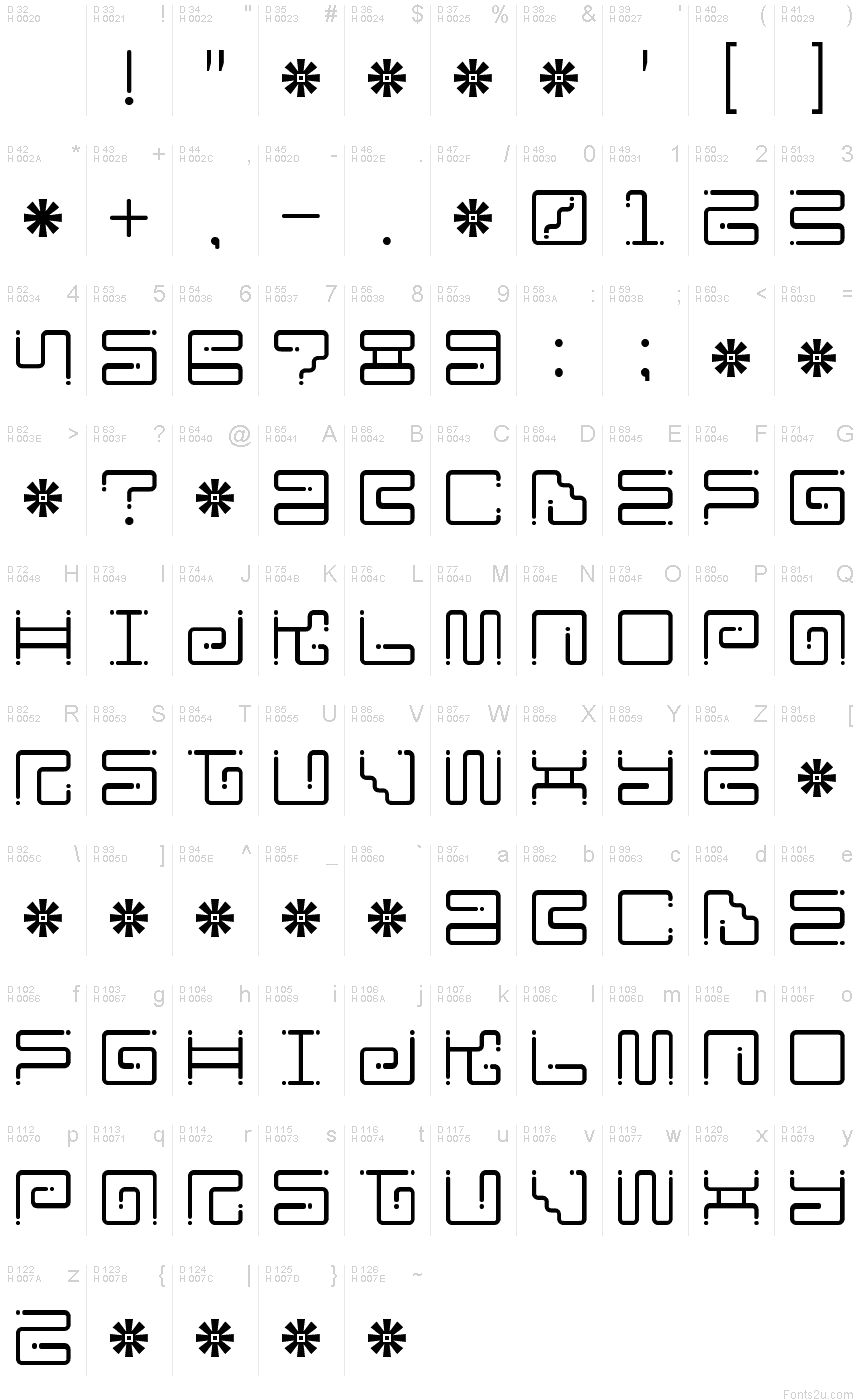
Iron Lounge Dots
Iron Lounge Dots di Jakob Fischer è un font display gratuito in stile groovy che ricorda dei tubi al neon piegati in morbidi anelli rettangolari. Le estremità puntinate e i tratti uniformi conferiscono a ogni parola un ritmo elettronico vivace, come un'insegna rétro che lampeggia fuori da un locale notturno. Le lettere sono morbide alla vista, ma abbastanza solide da sostenere titoli d'impatto che catturano l'attenzione.
Con Iron Lounge Dots, i titoli acquistano immediatamente un ritmo funky e futuristico, ideale per poster musicali, flyer per club, grafiche di gioco, packaging, miniature di YouTube e promozioni sui social media. Questo font gratuito dà il meglio di sé nei grandi formati, dove i suoi angoli arrotondati e i punti possono risaltare; abbinalo a un sans-serif geometrico per il testo principale, così da mantenere uno stile audace ma leggibile.